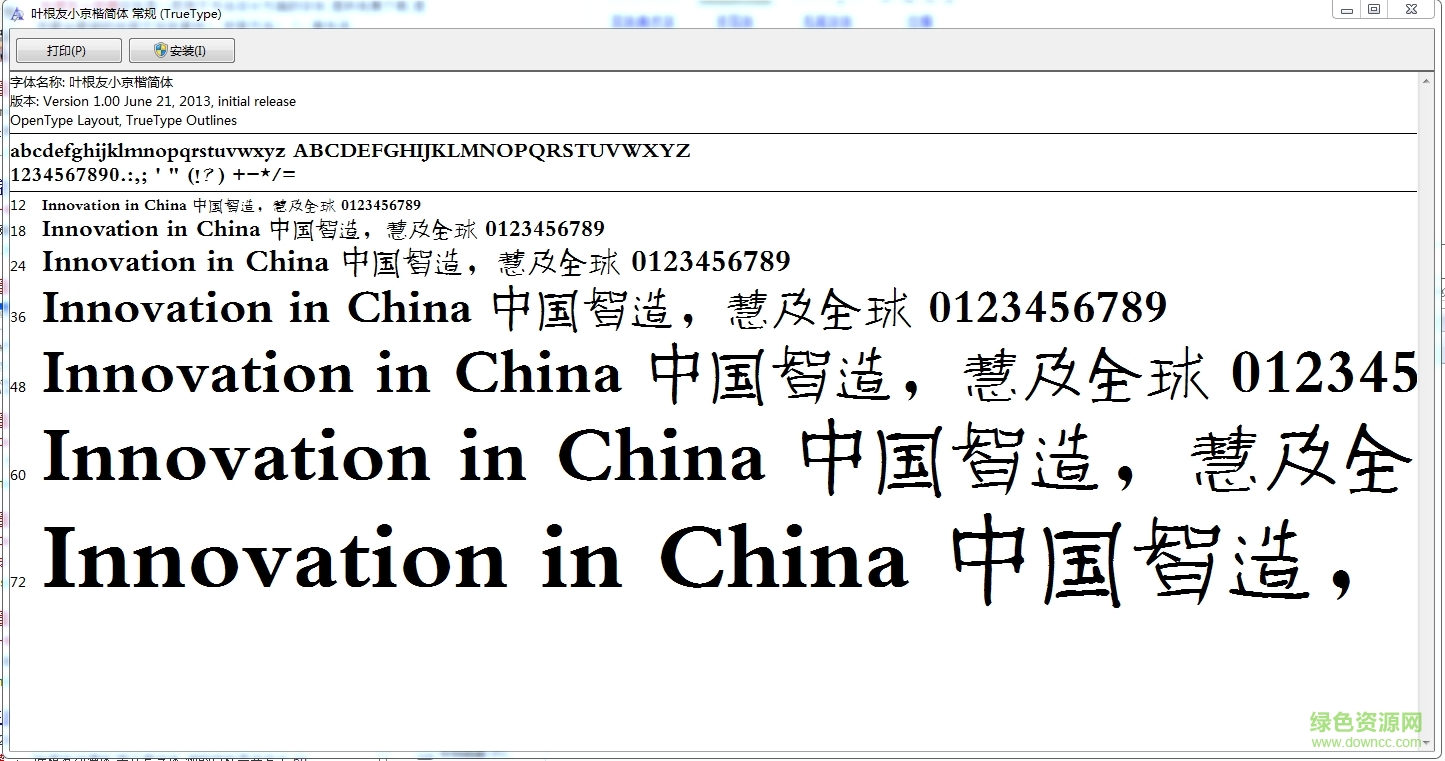
葉根友小京楷簡(jiǎn)體是由葉根友先生開發(fā)的一款應(yīng)用于藝術(shù)創(chuàng)作方面的中文簡(jiǎn)體漢字,該字體具備手寫效果,充滿兒童化,年輕化,效果非常好,可應(yīng)用于兒童繪畫、藝術(shù)創(chuàng)作、平面廣告、印刷包裝等領(lǐng)域,喜歡的小伙伴快來綠色資源網(wǎng)下載吧!